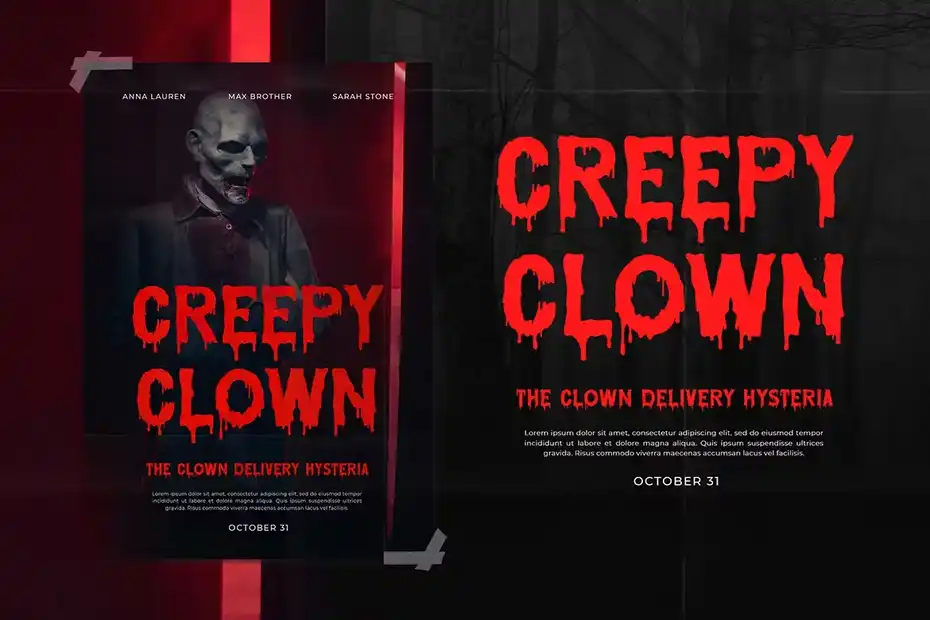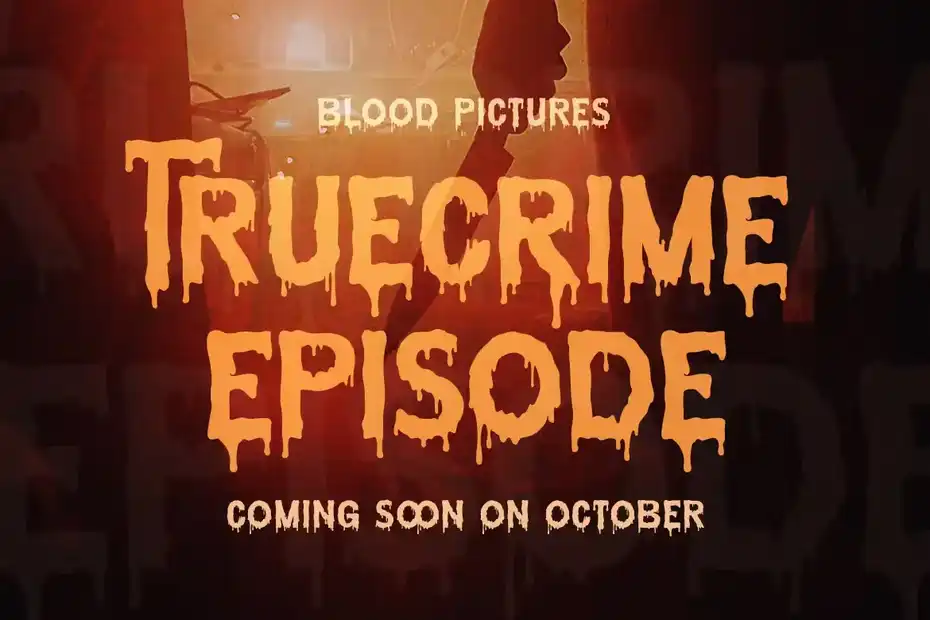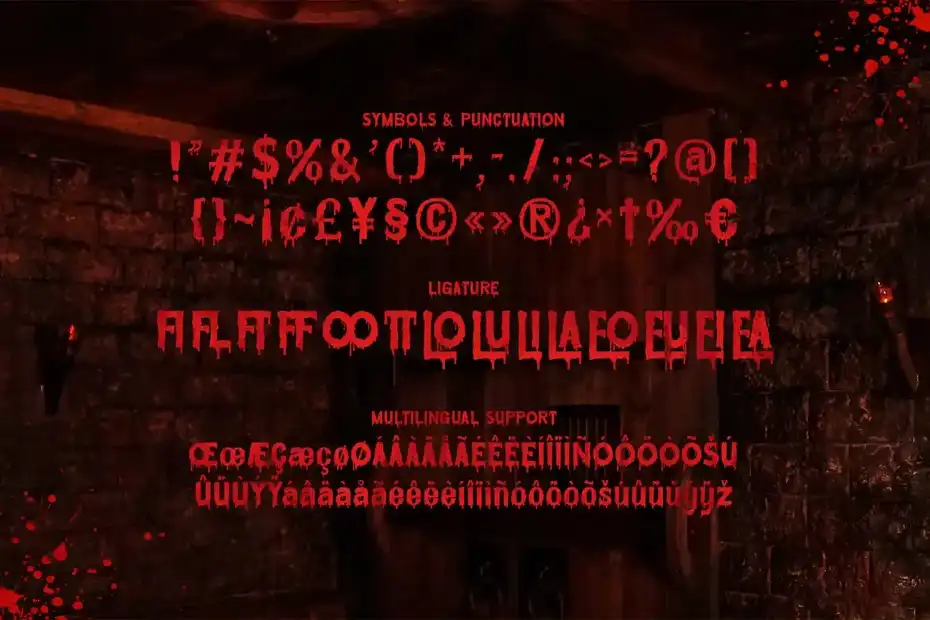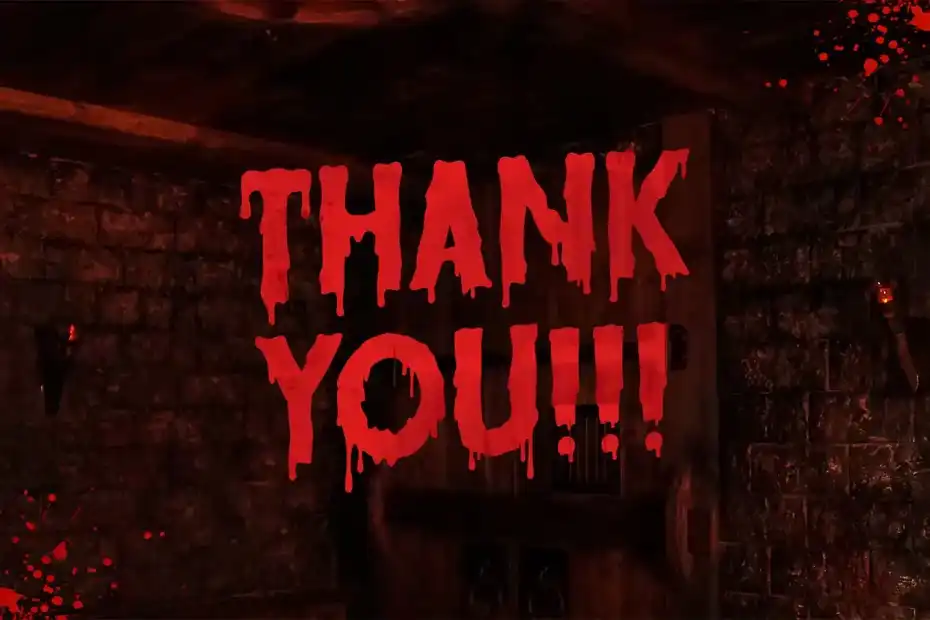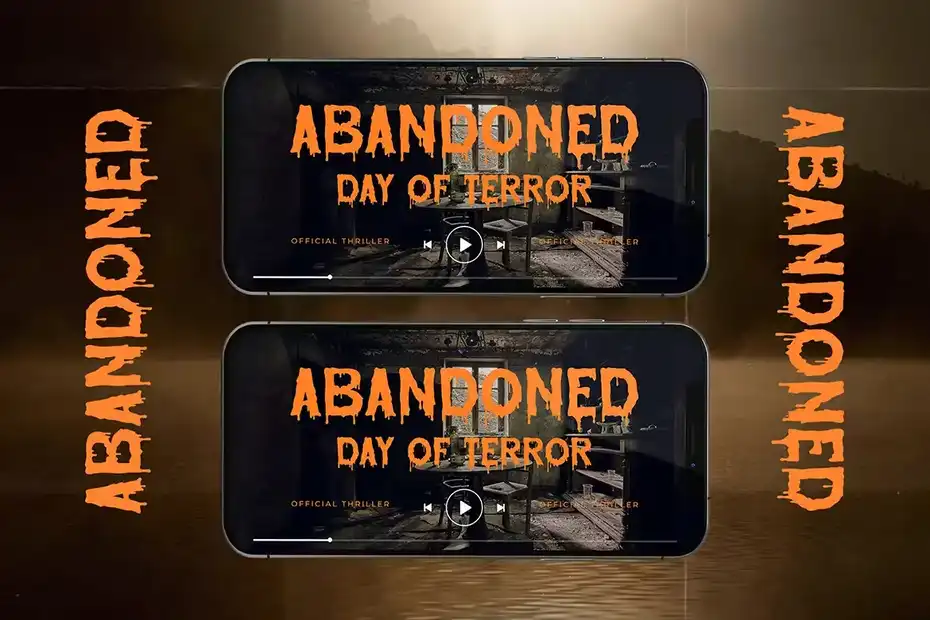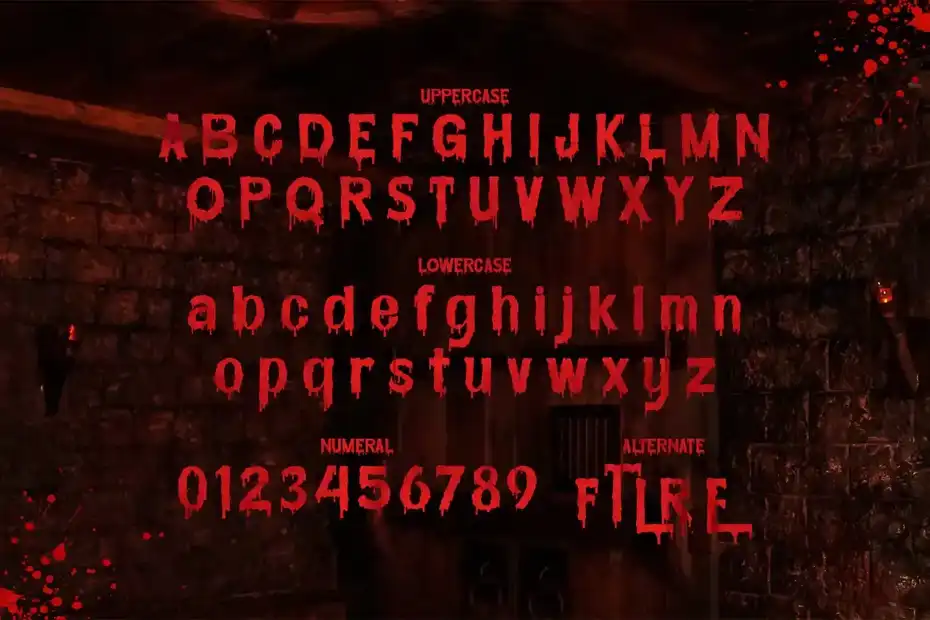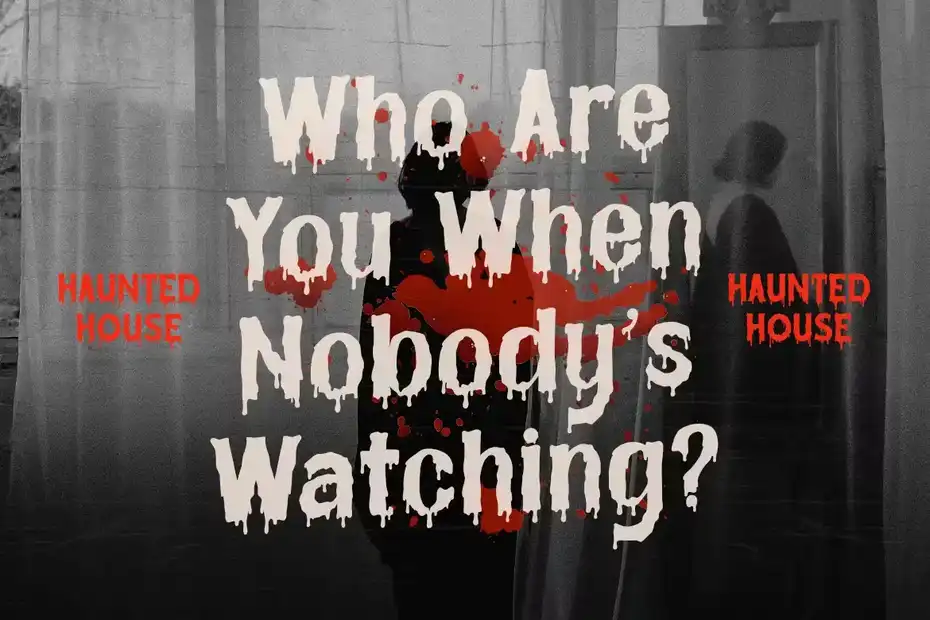
فونت انگلیسی ترسناک Grimes Blood – Scary Blood Font : این مجموعه شامل یک فونت انگلیسی ترسناک است که برای پوستر فیلم ترسناک، تیشرت و غیره مناسب میباشد.
- فضا بین حروف: معمولی
- اندازه بهینه: تمامی سایز ها